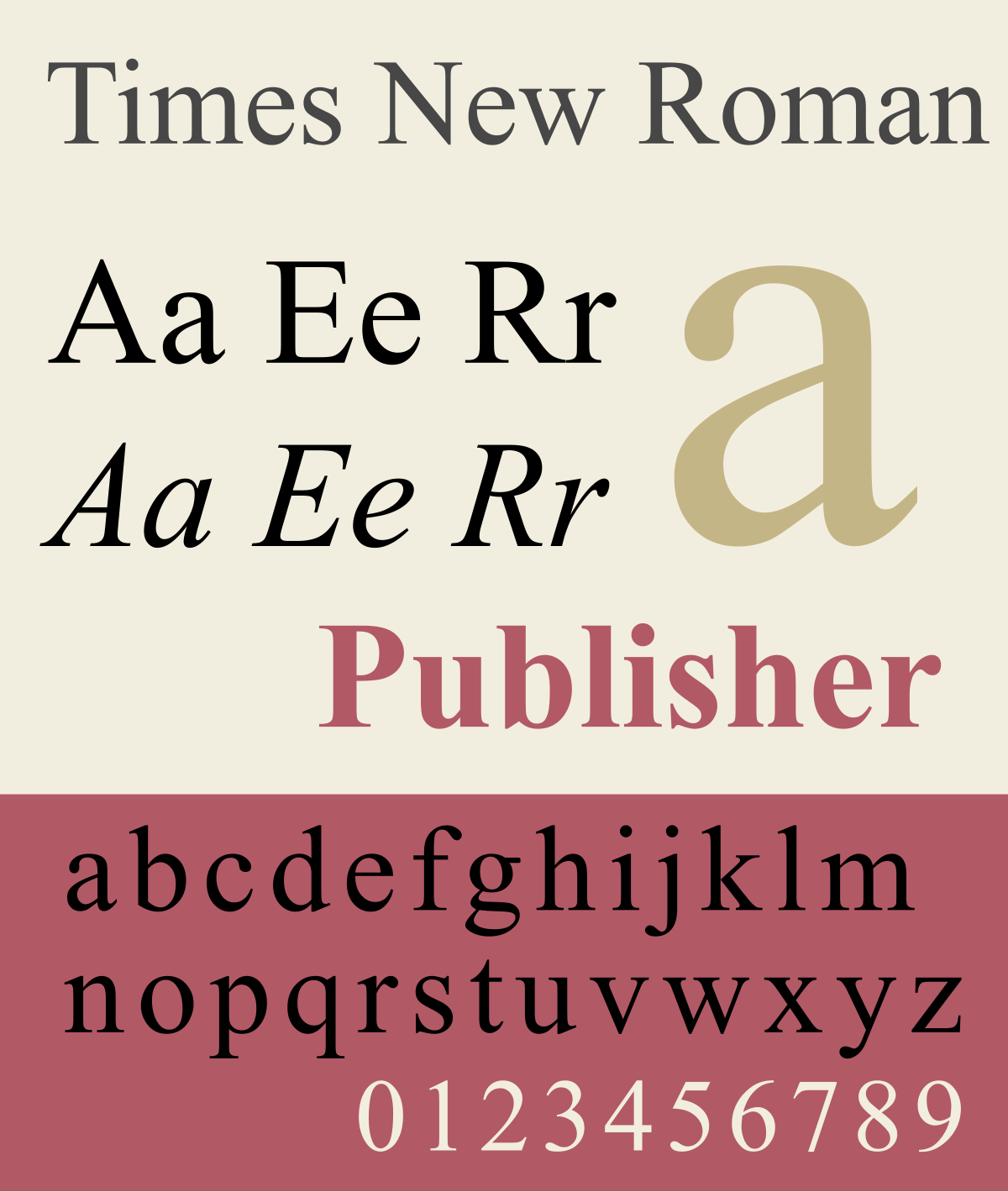
Ну думаю подойдет и Times New Roman, но хотелось бы TimesЗадача у вас какая, для чего шрифт? Чем Times New Roman не подходит?
Пока непонятно какой именно искомый, но с эппловским вроде есть даже в латиницемежду искомым Times
На картинки посмотри, вот если не найдешьМногабукаф
различия между искомым Times и Times New Roman?
есть даже в латинице
Подойдет для чего и почему хотелось бы Times? Уже есть файл с ним или что-то еще?
Для меня значимым является то, что у Таймс толщина штриха в обычном начертании чуть больше, а в полужирном чуть меньше чем в ТНР. То есть плотность текста в обычном выше и читаемость у Таймс на мой взгляд лучше, а полужирный не вываливается.различия есть — но я делал упор именно на слово значимые
Как-то не заметно на картинке вышеу Таймс толщина штриха в обычном начертании чуть больше
ТС вообще не сказал зачем и почему нужен не жить не быть Times, а вы копья ломаете.Для меня значимым является